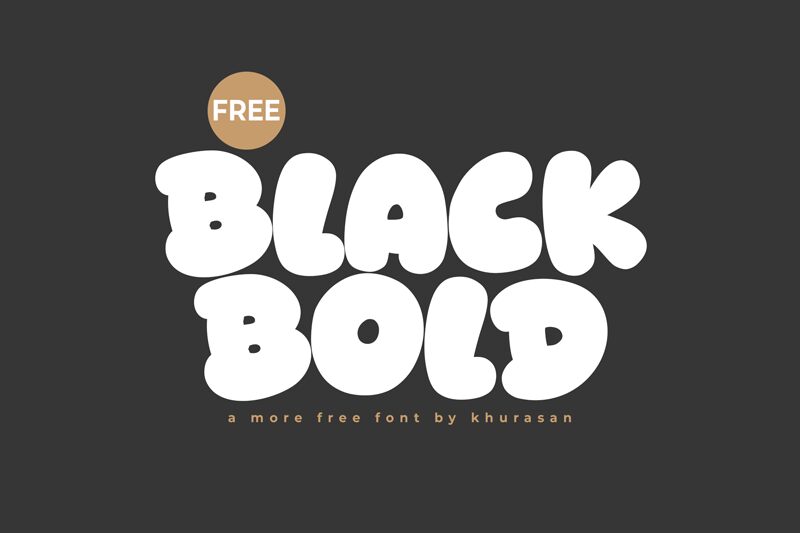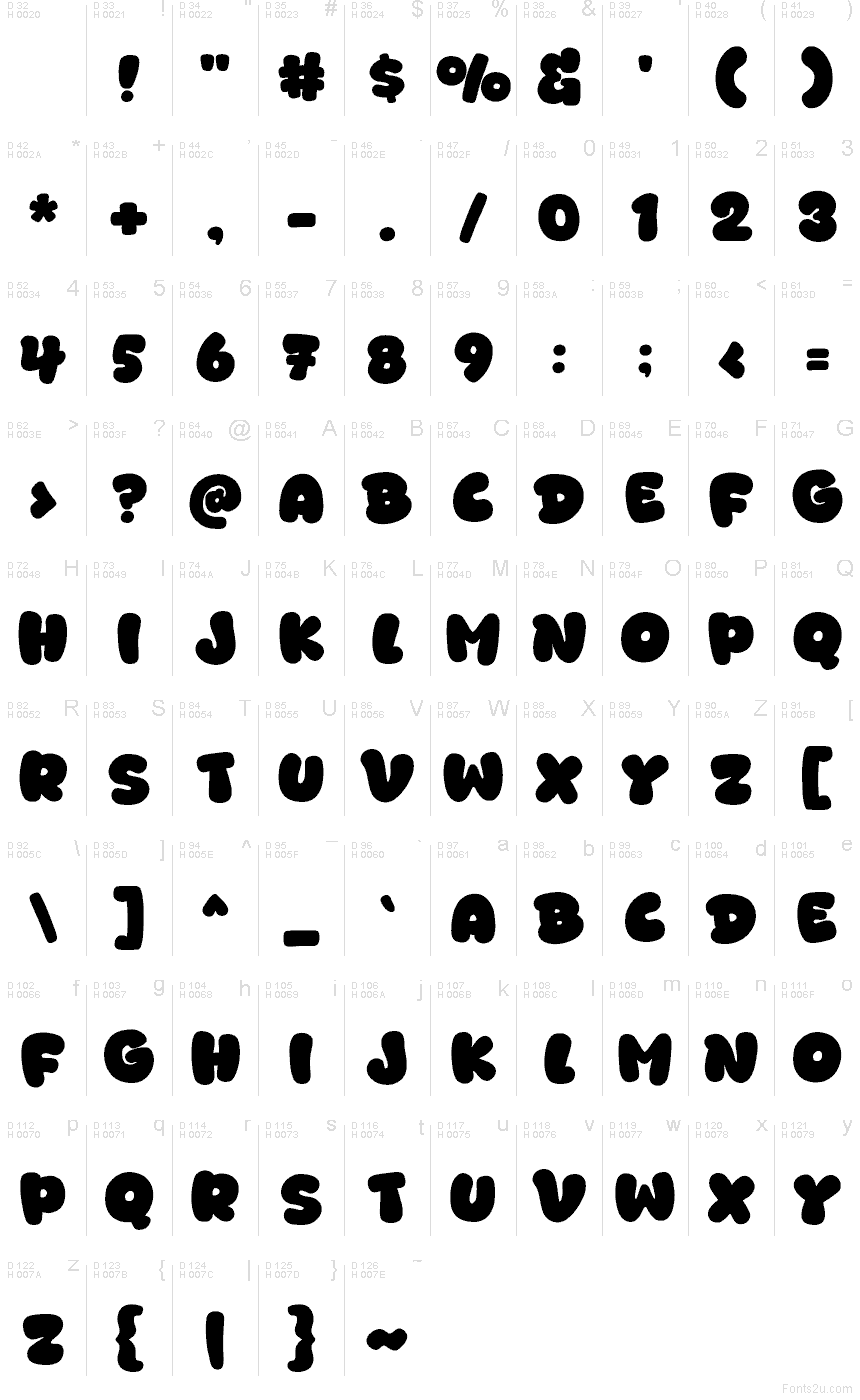
Black Bold od Khurasan je bezplatné kreslené display písmo. Jeho velká písmena s měkkými hranami působí jako nafouknuté gumové výřezy těsně u sebe. Zaoblené tvary, hluboké křivky a mírně nepravidelný rytmus dodávají fontu hravý komiksový nádech, aniž by působil zbytečně složitě.
Hodí se na obaly sladkostí nebo hraček, plakátové nadpisy, letáky na akce pro děti, náhledy na YouTube i na výrazný branding, kde musí přátelské, nadměrné slovo samo o sobě nést celou náladu. Jako bezplatný font funguje Black Bold nejlépe v krátkých, úderných nastaveních, jako jsou titulky nebo loga, protože jeho tlusté, bublinové tvary mluví samy za sebe.